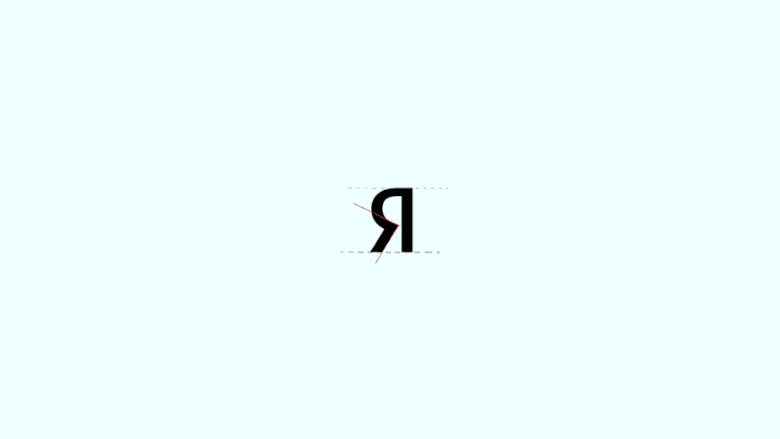
«Яндекс» сменил логотип и фирменный шрифт
«Яндекс» решил привести к единообразному виду айдентику всех своих сервисов. Для этого был создан новый логотип, набранный шрифтом, который разработан дизайнерами компании совместно с Ильёй Рудерманом (он давно сотрудничает с «Яндексом» и участвовал в разработке шрифта Yandex Sans).
Прежний логотип «Яндекса» был создан около 13 лет назад, когда компания занималась в основном интернет-проектами (прежде всего поисковиком и рекламной сетью) и не думала оказывать услуги в офлайне.
«Предыдущий логотип „Яндекса“ был создан почти тринадцать лет назад. Тогда никто не думал, что интернет-компания может заниматься доставкой продуктов, обрабатывать платежи и делать беспилотные автомобили. Новая айдентика отражает суть современного „Яндекса“ и хорошо выглядит на самых разных поверхностях, от экрана смартфона до пакета с продуктами из „Лавки“. В то же время она напоминает, что у сервисов „Яндекса“ общие технологии и общее начало — поиск», — Геннадий Лохтин, дизайн-директор «Поиска».
Новый логотип и шрифт будут использоваться как в интернет-сервисах «Яндекса», так и на объектах офлайн-бизнеса (например, на сумках курьерах «Яндекс.Еды» и автомобилях водителей «Яндекс.Такси»). Сокращённая версия логотипа — набранная новым шрифтом буква «Я» в красном круге.
«Яндекс» также изменил внешний вид поисковой строки, теперь она не оформлена в виде стрелочки.
Был Regular — стал Bold
Как-то «ндекс» теперь слишком давит, отвлекая внимание от и получившейся визуально более слабой «Я».